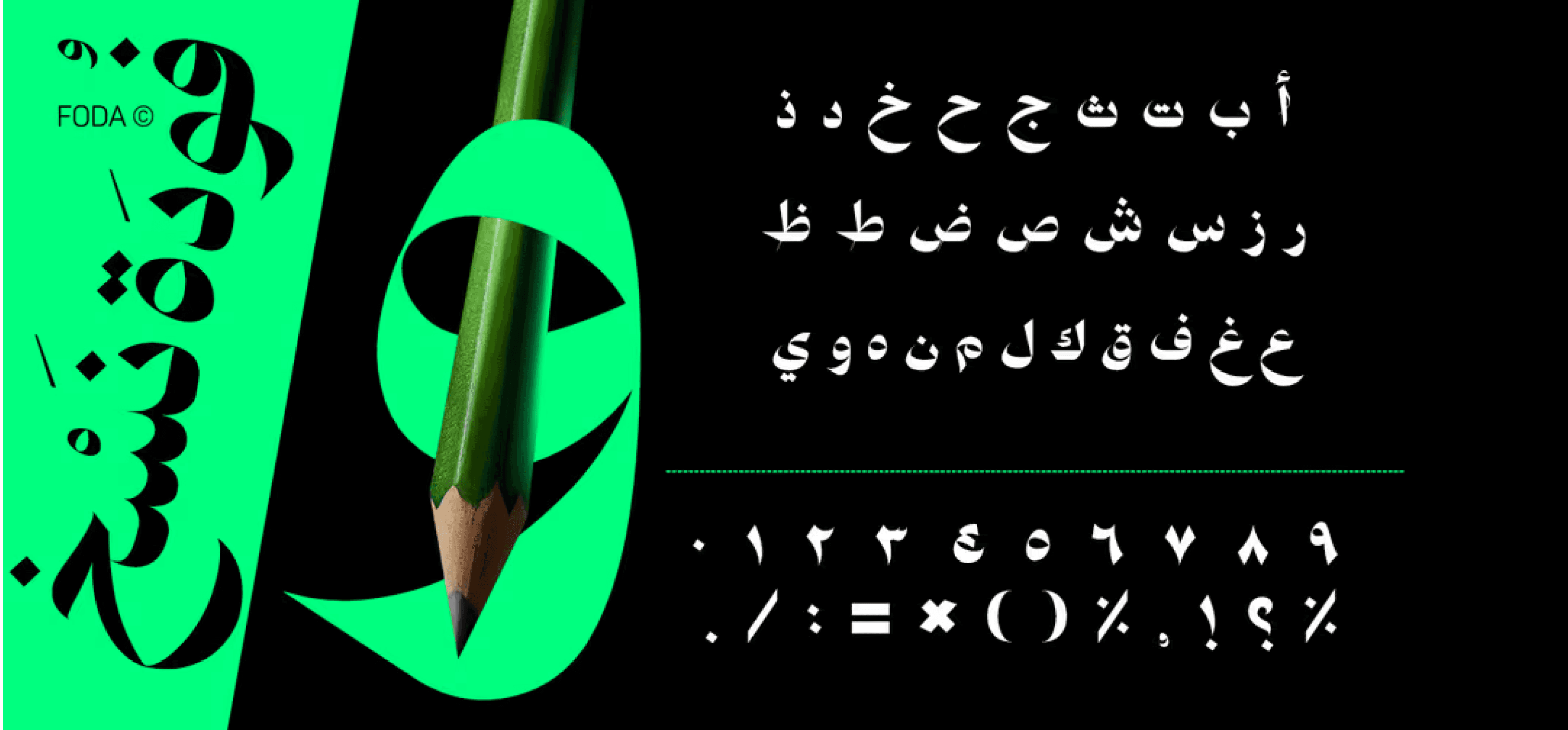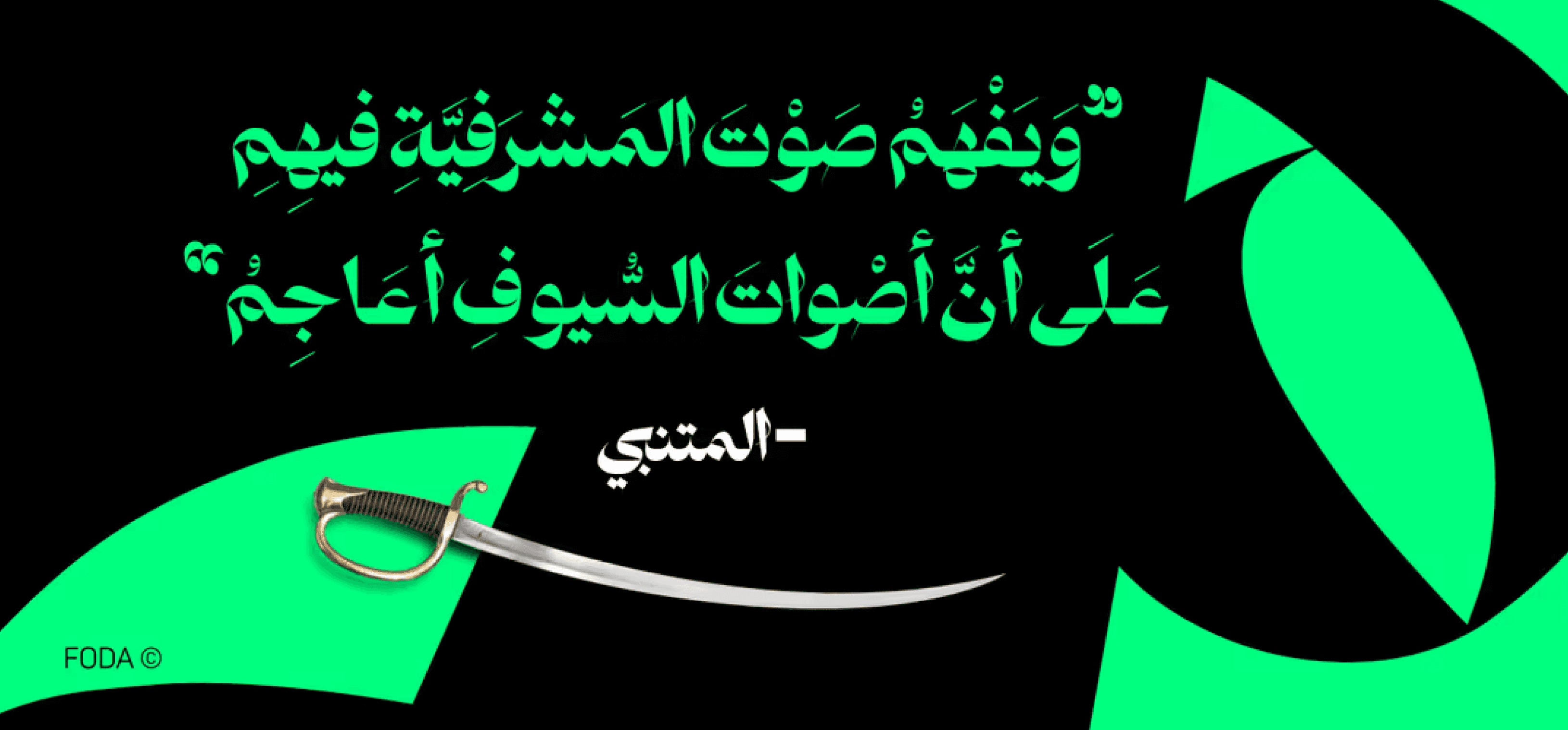
هو خط نسخ عصري يجمع بتناغم بين الأصالة والحداثة، حيث يُبرز جمال الحرف العربي مع الحفاظ على وضوح القراءة وسلاستها.
يُعد خيارًا مثاليًا لكتب القراءة، والصحف، والعناوين، والمجلات، والشعر، والفقرات النصية الطويلة والقصيرة، وغيرها من الاستخدامات الطباعية المتنوعة.
هو خط نسخ عصري يجمع بتناغم بين الأصالة والحداثة، حيث يُبرز جمال الحرف العربي مع الحفاظ على وضوح القراءة وسلاستها.
يُعد خيارًا مثاليًا لكتب القراءة، والصحف، والعناوين، والمجلات، والشعر، والفقرات النصية الطويلة والقصيرة، وغيرها من الاستخدامات الطباعية المتنوعة.
هو خط نسخ عصري يجمع بتناغم بين الأصالة والحداثة، حيث يُبرز جمال الحرف العربي مع الحفاظ على وضوح القراءة وسلاستها.
يُعد خيارًا مثاليًا لكتب القراءة، والصحف، والعناوين، والمجلات، والشعر، والفقرات النصية الطويلة والقصيرة، وغيرها من الاستخدامات الطباعية المتنوعة.